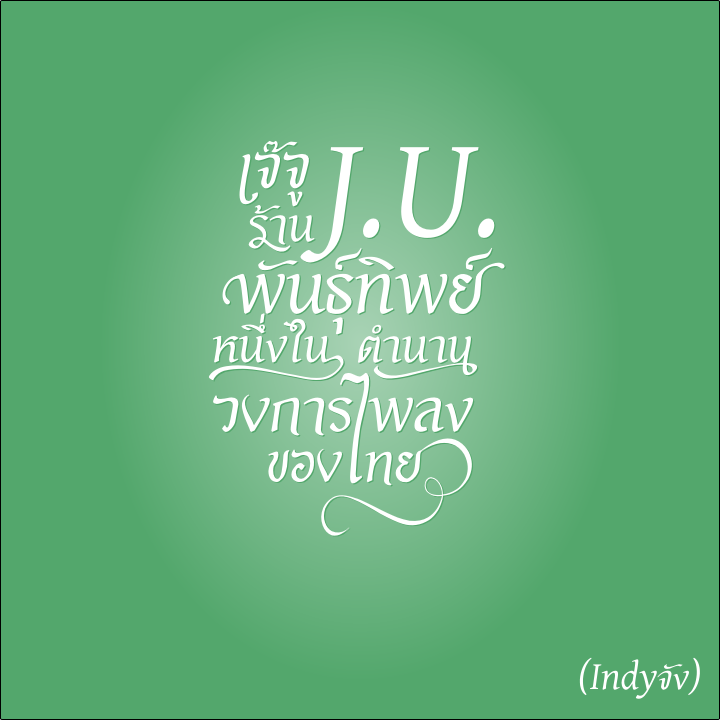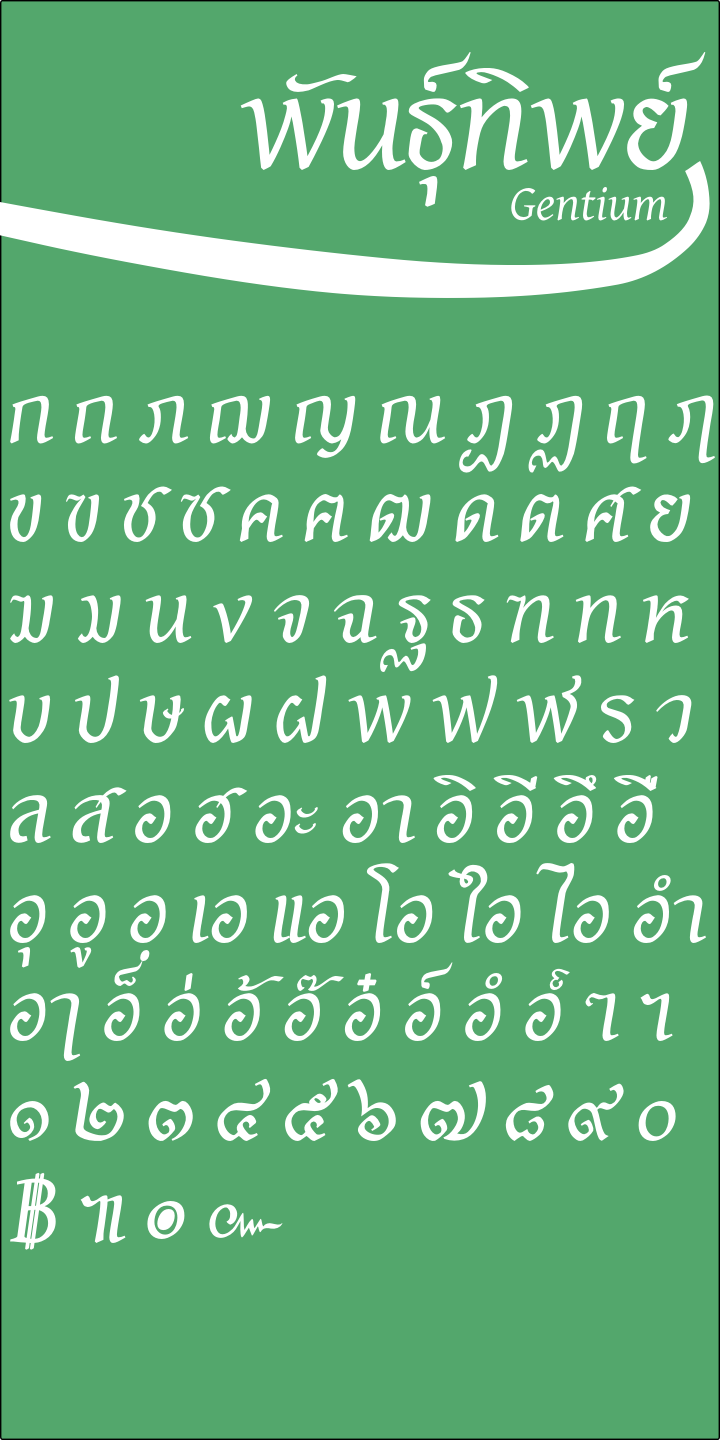
ฟอนต์พันธุ์ทิพย์
งานทดลองทำฟอนต์ ต่อหัว ต่อหาง นี้  เกิดเนื่องจากผมชอบฟอนต์ลูกทุ่งที่เล่นหางมาก หางยาวๆ สวยดี แต่ก็มาพบว่าบางทีหางยาวๆมันไป ทับสระอุ สระอู พอดี เลยอยากลองทำหางหลายๆความยาวดู .. เก็บไว้ในใจ   :15:
วันนึงนั่งรถติดอยู่ประตูน้ำ เงยหน้ามองขึ้นไปเห็นภาพประมาณนี้เลยฟอนต์พันธุ์ทิพย์สวยดีแฮะ เลยลองแกะดู พบว่าจะทำได้ ต้องทำฟอนต์
ตัวซ้ำๆกัน แต่มีหัว และหางที่แตกต่าง .. งานเข้า  :38:
เริ่มจากหา English Font ต้นแบบที่ใกล้เคียง ผมเลือก Gentium Normal Italic (https://www.fontsquirrel.com/fonts/Gentium-Basic) มาใช้งาน เพราะเขาอนุญาตให้ใช้ได้
จากนั้นทำฟอนต์ไทยประกบจนหมด ได้เป็น SOV_Pantip_Gentium เป็นฟอนต์พื้นฐาน
แล้วเริ่มทำฟอนต์เฉพาะ และตัวพิเศษ เป็นหัว และหาง เพื่อให้หน้าตาคล้าย "พันธุ์ทิพย์ พลาซา" ได้เป็น SOV_Pantip_Special
จากคำแนะนำของเพื่อนสมาชิก จึงทำเป็น ฟอนต์ที่มีหัว หรือหาง มาให้เฉพาะเลย เพื่อให้มีหน้าคาคล้าย "พันธุ์ทิพย์ พลาซา" ได้เป็น SOV_Pantip_Extra
จัดช่องไฟ และความเป็นระเบียบโดยรวม
จากนั้นก็แอบทำตามที่เคยคิดไว้ เรื่องต่อหางหลายความยาว ใน SOV_Pantip_Special
คราวนี้ฟอนต์ยังว่างอีกเยอะ เลยทำหัวหางมั่วไปหมด รวมถึงตัวอิสระด้วย เอามาจากสารพัด free vector มั่วเละเลยคราวนี้
หน้าตาทั้งสามฟอนต์ครับ
ฟอนต์ภาษาอังกฤษเอามาจากต้นฉบับ ไม่ดัดแปลงเลย ยกเว้นย่อขนาดให้เข้ากับ template ครับ.. กราบขอบพระคุณอีกครั้ง
ฟอนต์ Pantip Gentium ใช้เป็นตัวอักษรยืนพื้นเวลาพิมพ์
ฟอนต์ Pantip Extra ใช้เปลี่ยนตัวอักษรให้มีหัว มีหาง แต่ใช้ได้เฉพาะบางตัวอักษร ตามรูปครับ
ฟอนต์ Pantip Special สำหรับงาน Graphic โดยเฉพาะ ไม่เหมาะกับงานเอกสาร หรือทำ web ที่ต้องเก็บเข้าระบบ computer นะครับ
เพราะมีการนำเอาตัวอักษรภาษาอังกฤษ มาใช้เป็นรูป หากเก็บในระบบจะทำให้ผิดความหมายได้
แต่ถ้าเอามาใช้ในงาน Graphic หรือ Presentation ที่เป็นรูป ก็น่าจะพอไหว
วิธีใช้ ปรับตามที่เพื่อนสมาชิกแนะนำ โดยใช้วิธีของอ.ธงชัย ให้เอา SOV_Pantip_Gentium เป็นฐานก่อนนะครับ แล้วค่อยเปลี่ยนเป็น SOV_Pantip_Extra สำหรับตัวหัวท้ายที่ต้องการ (บางตัวเป็นหัว บางตัวเป็นท้าย ลองดูที่ตัวอย่างฟอนต์นะครับ)
1. เรื่องหางยาวนี่ ได้รับอิทธิพลจาก ฟอนต์ บางลี่โฆษณา http://www.f0nt.com/release/blk-bangli-ko-sa-na/
2. เรื่องหางระโยงระยางนี่ ได้รับอิทธิพลเต็มๆมาจาก ฟอนต์ แก้วเพชร ของ อ.ธงชัย ศรีเมือง http://www.f0nt.com/release/ts-kaewpet-np-ts-kaewpet-extra-np/
3. ตัวเลขไทยชุดนี้ ต้นแบบมาจาก ฟอนต์ ศรีนคร ของ อ.ธงชัย ศรีเมือง
4. ต้นแบบภาษาอังกฤษ Gentium https://www.fontsquirrel.com/fonts/Gentium-Basic
5. google ที่หาคำว่า swashes ทำให้ได้ font, vector และแนวคิดเรื่อง หัว หาง อีกเพียบ
เพิ่มเติมเส้นระโยงระยางได้นี่ ผมนึกถึง อ.ธงชัย ศรีเมือง ขึ้นมาทันทีเลยนะ
แล้วก็อีกงานนึงที่นึกถึง คืองานปกอัลบั้ม "พวงร้อย"
ผมไม่รู้ว่าปกอัลบั้มนี้ออกแบบใน พ.ศ. ใด แต่ถ้าเป็นต้นๆ พศ.2500's ตามช่วงเวลาที่อัลบั้มนี้ออก นี่
ผมว่างานนี้ Modern มากๆ ในยุคนั้น
ใช่ครับ เรื่องหางระโยงระยางนี่ ได้รับอิทธิพลเต็มๆมาจาก ฟอนต์ แก้วเพชร ของ อ.ธงชัย แต่ความเนียนงามของผม ยังห่างไกล
ต้องฝึกเรื่อง vector อีกเยอะครับ  แถมตัวเลขไทยชุดนี้ ก็เอาต้นแบบมาจาก ฟอนต์ ศรีนคร (ขออภัย ไม่ได้แจ้ง credit ไว้ด้วย  :46:)
นอกจากฟอนต์สวยงามแล้ว แนวคิดการแก้ปัญหา การนำไปใช้งานของ อ.ธงชัย ก็ถือเป็นสุดยอดครับ การทำฟอนต์ -Extra และ Bold นี่
ตอบโจทย์เรื่องการต้องจำ ตัวอักษรพิเศษจริงๆ
ส่วนเรื่องหางยาวนี่ ได้รับอิทธิพลจาก ฟอนต์ บางลี่โฆษณา ครับ  เห็นครั้งแรกถึงกับอึ้ง..รักเลย :10:
ฟอนต์คำว่า พวงร้อย สวยมากครับ แนวคิดการดัดตัวอักษรละติน มาเป็นอักษรไทย และเพิ่มอัตตลักษณ์เข้าไปนี่ ยังคงมีอยู่ทุกยุคสมัยนะครับ
โอ้ น่าสนใจครับ Gentium เป็นฟอนต์เสรีในตำนาน ทั้งในแง่ความงามและการรองรับหลากหลายภาษา เติมตัวไทยเข้าไปน่าจะดี http://software.sil.org/gentium/
แต่ผมไม่เห็นด้วยที่มีฟีเจอร์ให้ป้อนตัวอักษรเพิ่ม เพราะมันบิดเบือนข้อมูลสำหรับคอมพิวเตอร์ ถ้าฟอนต์ใช้สำหรับโปรแกรมทำภาพกราฟิคอย่างเดียวคงไม่มีปัญหา แต่ถ้าใช้ในเอกสารมันคือเรื่องใหญ่นะครับ มัน spoil ผู้ใช้ (เช่น ฟอนต์บาลีที่เปลี่ยนสระอึเป็นสระอิบวกนิคหิต หรือ ฟอนต์ที่เปลี่ยนเลขอารบิคเป็นเลขไทย มันทำให้ผู้ใช้ป้อนข้อมูลไม่ถูกต้องตามโค้ดพอยน์ของตัวอักษร) เพราะข้อมูลที่คอมพิวเตอร์บันทึกมันต่างจากที่ตามนุษย์เห็น สมมติมีคนเอาไปใช้เป็นฟอนต์ในเว็บแล้วเขาพิมพ์ตัว q หรือ t เพื่อเติมหัวเติมหาง search engine มันก็เก็บตัว q & t เพิ่มเข้าไปด้วยนะครับ หรือถ้าใช้กับพวก text file เวลาเปลี่ยนฟอนต์ก็คงลำบาก เพราะมันมีตัวอื่นเกินมา
ฟอนต์รุ่นก่อน OpenType เค้าแก้โดยแยกไฟล์ฟอนต์เป็น variants ครับ เช่น Small Caps, Swash เวลาจะเปลี่ยนสไตล์ตัวอักษรก็เปลี่ยนฟอนต์ประมาณนั้น (เหมือนเปลี่ยนน้ำหนัก) อย่าง Mrs Eaves คนทำฟอนต์ลำบากกว่าคนใช้ฟอนต์แน่ๆ แต่วิธีนี้ใช้ได้กับทุกโปรแกรมที่เปลี่ยนฟอนต์ได้